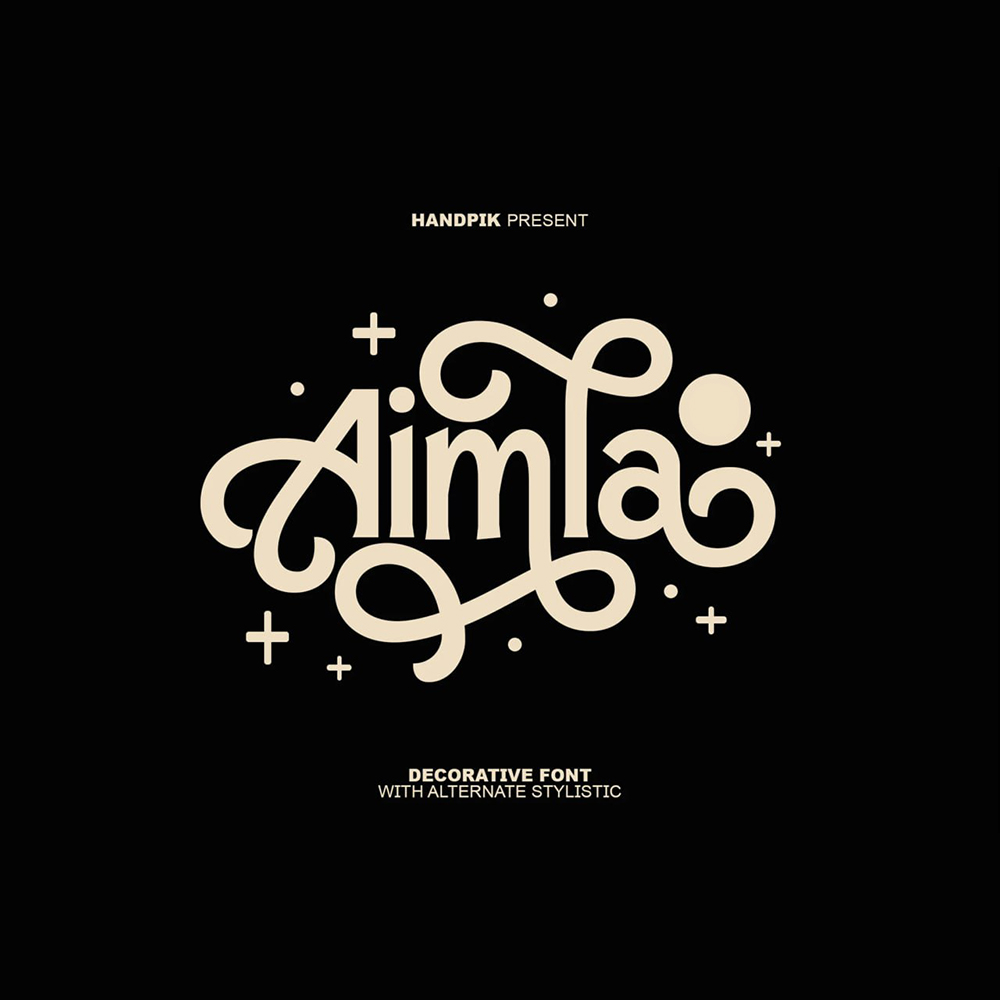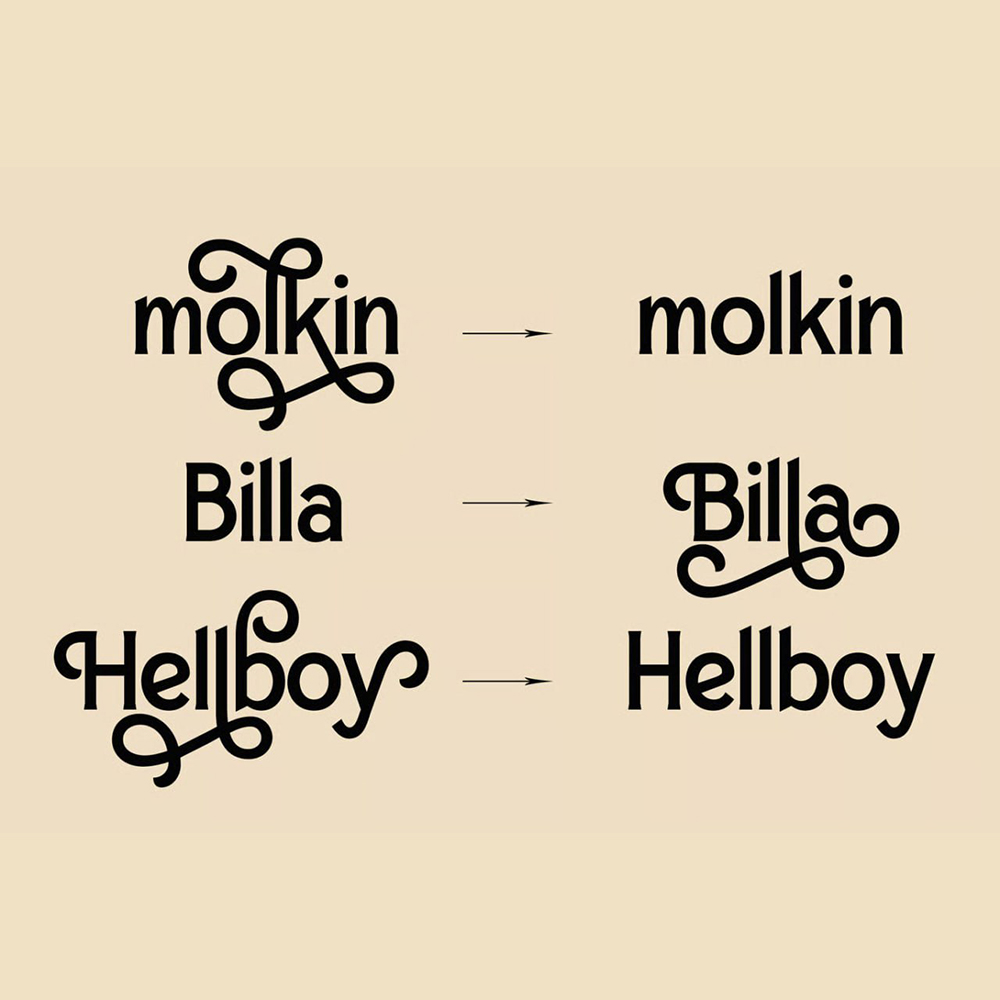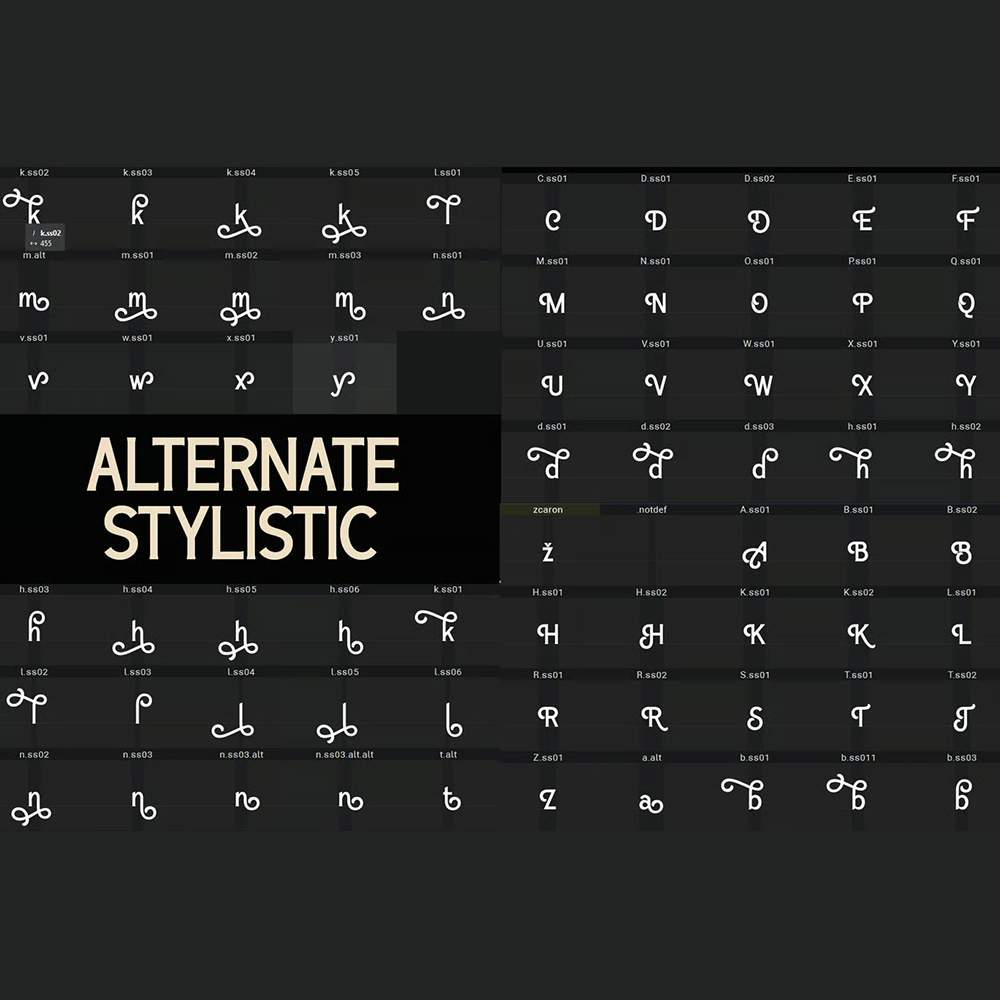
دانلود فونت انگلیسی Aimla Font
فونت پرمیوم و انگلیسی Aimla Font برای بسیاری از پروژهها مانند کتاب، مجله، لوگو، برندسازی، عکاسی، نقل قولها، هدر وبلاگ، پوستر، تبلیغات و غیره عالی خواهد بود.
مزایای استفاده از فونت لاتین Aimla چیست؟